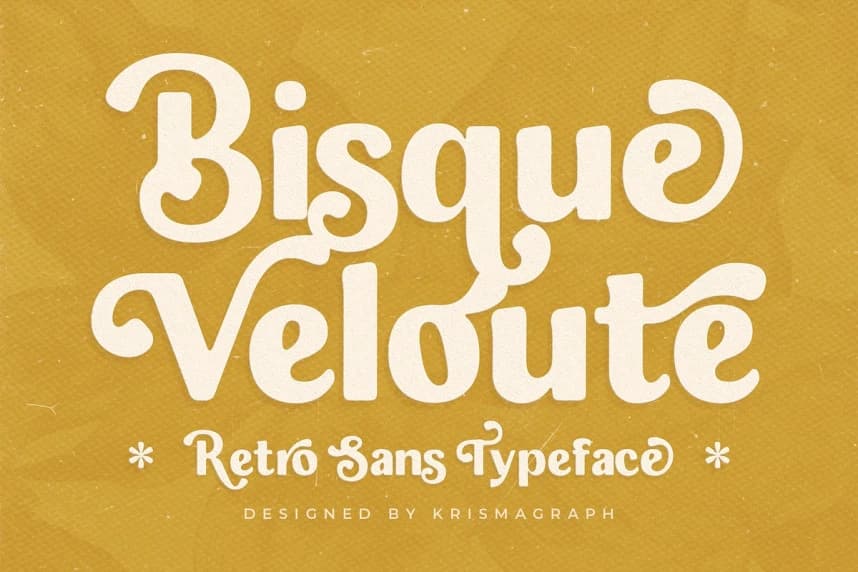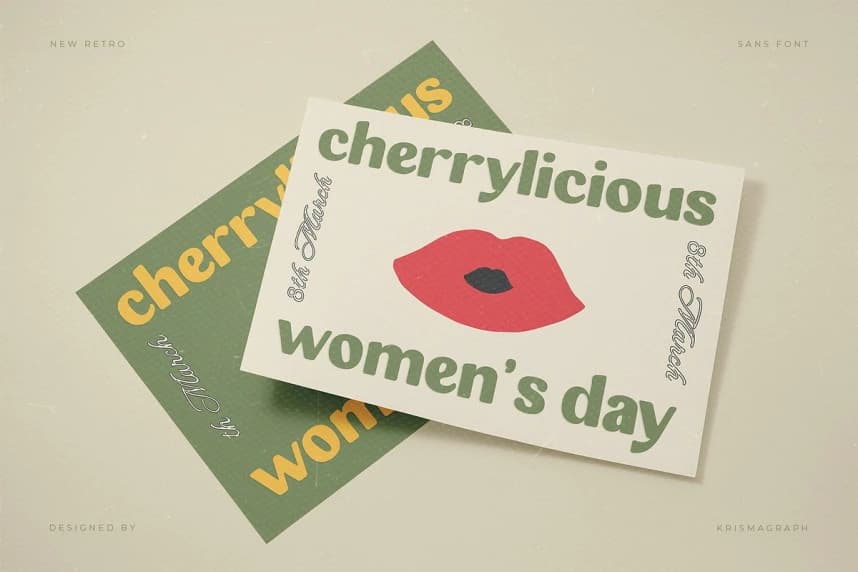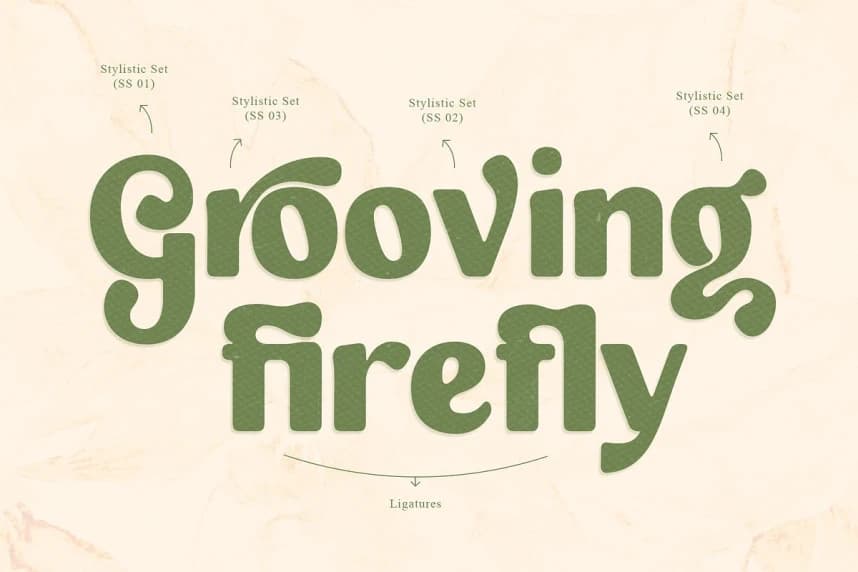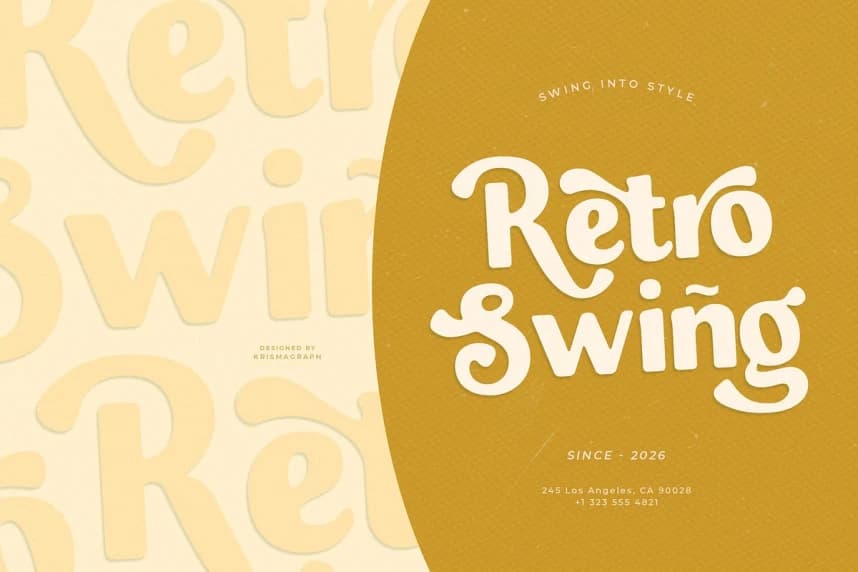
Bisque Veloute Font
Bisque Velouté Font, cesur ve neşeli bir retro sans tipografisidir; 1960'lar ile 1970'lerin groovy ruhunu belirgin bir modern duyarlılıkla yansıtır. Kalın, akıcı harf biçimleri — dönmüş uçlar ve kabarcıklı eğrilerle tamamlanmış — kesinlikle sıcak bir etki yaratır.